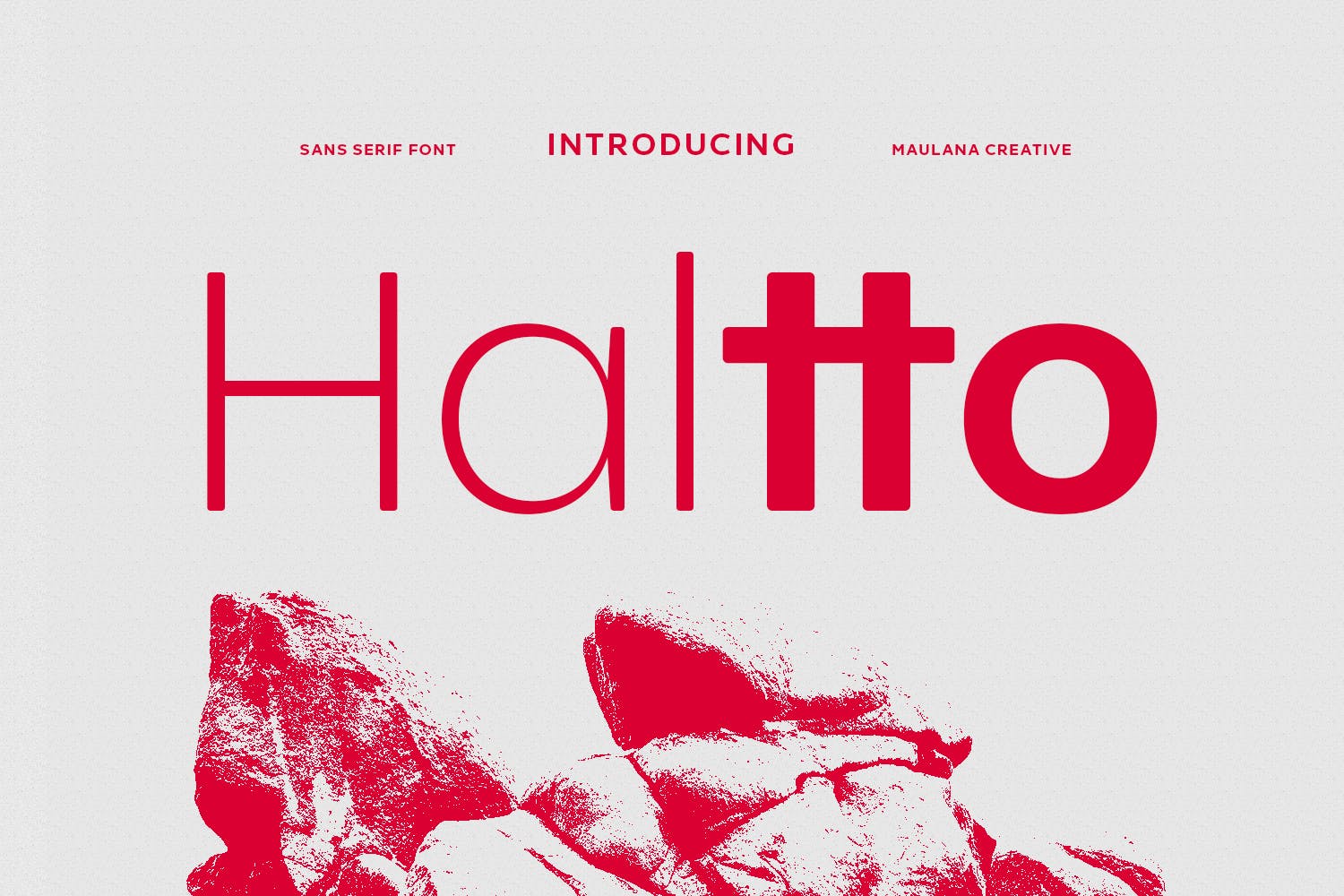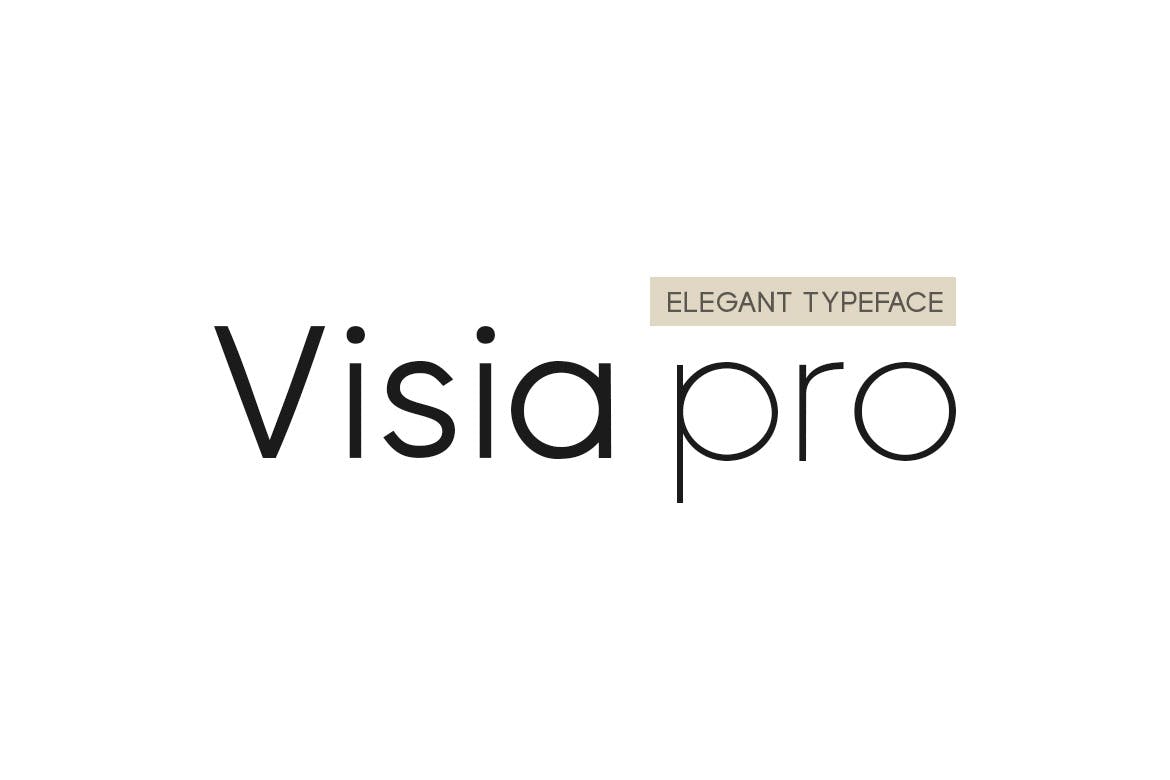
20+ Beste Fonts ähnlich der Century Gothic
20+ Beste Schriften Ähnlich wie Century Gothic
Die hohe ‚x‘-Höhe und das saubere, moderne Buchstabendesign machen Century Gothic zu einer der begehrtesten Schriften für Designer. In dieser Sammlung gehen wir über diesen klassischen Look hinaus, um Schriften zu finden, die Century Gothic ähneln, aber auch kreativere und originellere Designs haben.
Da Century Gothic auf Microsoft-PC-Geräten kostenlos verfügbar ist, wurde die Schrift weit verbreitet in allen Arten von Designs verwendet. Wir haben diese Sammlung von Century Gothic-Alternativen für diejenigen von Ihnen erstellt, die eine professionellere und einzigartigere Schrift suchen, um sich von der Masse abzuheben.
Hier haben wir eine unglaubliche Liste zusammengestellt, die sowohl kostenlose als auch kostenpflichtige Schriften mit Merkmalen enthält, die Century Gothic stark ähneln. Unsere Sammlung dient als erschwingliches Toolkit für Designer, die diese vertraute Luft von Professionalität suchen, die Century Gothic mit sich bringt. Perfekt geeignet für eine Vielzahl von Designprojekten erfassen diese Schriften mehrere Designelemente, die Ähnlichkeiten mit der originalen Standardschrift aufweisen.
Lassen Sie uns eintauchen und einen Blick darauf werfen.
Hempa Sans
Hempa Sans ist eine schlanke, moderne serifenlose Schriftfamilie mit 16 Stilen, die im Design Century Gothic ähnelt. Mit einer feinen Mischung aus 8 aufrechten und 8 abgewinkelten Designs haben die Schöpfer darauf geachtet, abwechslungsreiche Zeichen in den Buchstaben (G,M,R,g,k,r,t,u,y) und starke Open-Type-Funktionen einzuführen. Geeignet für Grafikdesign und Anzeigeverwendung, wird es als OTF-, TTF- und Webfont-Dateien geliefert.
Haltto
Haltto ist eine einzigartig geometrische, serifenlose Schrift mit verspielten Zeichen, die an Century Gothic erinnern. Mit zwei Strichgewichten und zahlreichen Ligaturen und Alternativen unterstützt sie über 100 Sprachen. Geeignet für verschiedene Anwendungen, von Logos und sozialen Medien bis zu Filmtiteln und Buchtiteln, fügt Haltto jedem Projekt eine kreative Note hinzu.
George Sans
George Sans ist eine moderne, serifenlose Schriftfamilie mit 8 einzigartigen Schriftarten, die die sauberen, stilvollen Linien der europäischen Geometrie widerspiegeln. Geeignet für verschiedene Anwendungen – vom Branding bis zur Beschilderung – funktioniert diese vielseitige Schriftfamilie besonders gut bei größeren Anwendungen. Das Paket enthält Groß- und Kleinbuchstaben, Zahlen, Satzzeichen und unterstützt mehrere Sprachen in OTF-, TTF- & WOFF-Formaten.
Metrisch
Metrisch ist eine moderne, serifenlose Schriftart, die nach den Prinzipien geometrischer Konstruktion entworfen wurde. Diese umfangreiche Schriftfamilie umfasst sieben Gewichte mit aufrechten Kursiven, maßgeschneidert für Anwendungen von Modeeditorial bis hin zu Logos und Beschilderung. Ihre Funktionen wie saubere vertikale Schnitte, optimierte Ecken und erweiterte lateinische Diakritika verleihen ihr ein glattes, raffiniertes Aussehen und Vielseitigkeit.
LORIN
LORIN ist eine schlanke, moderne geometrische Sans-Serif-Schrift ähnlich wie Century Gothic, aber mit ihrem eigenen einzigartigen Charme und Stil. Mit vier unterschiedlichen
Gewichten von leicht bis extra fett ist LORIN vielseitig für jede Art von Inhalt, von Logos bis hin zu Überschriften und sogar großen Postern. Ihre ästhetische Anziehungskraft macht sie ideal für hochwertige Modewebseiten und minimalistische Portfolios.
Devina Rodent
Devina Rodent ist eine serifenlose Schriftfamilie mit einem auffallend modernen Touch im klassischen Century Gothic-Stil. In neun verschiedenen Gewichten erhältlich, balanciert diese vielseitige Schriftart männliche und weibliche Qualitäten aus und ist damit für eine Vielzahl von Projekten geeignet. Von Briefpapier und Logos bis hin zu Modebranding und Buchumschlägen verspricht Devina Rodent Klasse und Eleganz in jedem Strich.
Altone
Altone ist eine kreative Schrift, die einen konventionellen geometrischen Look ohne Serifen bietet, um die Lesbarkeit und vielseitige Verwendung zu verbessern. Sie zeigt eine einfache, fette und solide Persönlichkeit, die eher dem Grotesk als dem klassischen Bauhaus-Stil zuneigt. Altone ist in der Breite moderat, mit flacher Spitze und geraden Strichen. Die Schrift kommt in 9 Gewichten mit passenden Schrägen.
VISIA Pro
VISIA Pro ist eine bemerkenswerte geometrische Sans-Serif-Schriftart, die dem Design von Century Gothic ähnelt. Entwickelt von Fontastica und vertrieben von Designova ist sie eine ideale Schriftart für verschiedene Anwendungen, einschließlich Logos, Überschriften und Branding im Web und Print. Mit 7 Gewichten von Extra Light bis Heavy bietet sie auch kursive Versionen jeder Gewichtsklasse und umfasst OTF-, TTF- und Webfont-Formate.
Invisible
Invisible ist eine geometrische serifenlose Schriftfamilie, die an Century Gothic erinnert. Mit neun Gewichten von dünn bis schwarz und einem dazugehörigen geneigten Stil bietet sie perfekt proportionierte Zeichen für Text und dicke, fette Zeichen für die Betonung. Mit ihren glatten Formen verleiht sie Ihren Designs Vielseitigkeit und eine einzigartige Note.